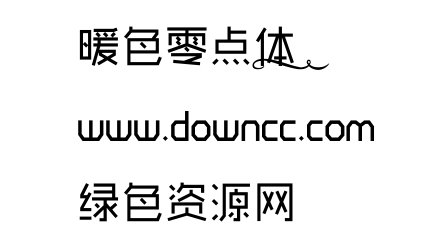
零點(diǎn)體是暖色君推出的一款藝術(shù)字體,在合體字體的基礎(chǔ)上添加了各種不同的修飾,讓文字變得個(gè)性十足,比起端正的宋體和楷書,顯得十分活潑,喜歡的歐陽(yáng)就來綠色資源網(wǎng)下載吧!
暖色零點(diǎn)體是由暖色君制作分享的卡通字體,字體間又裝飾上了漂亮的花紋,更加具有藝術(shù)感,將黑體字體進(jìn)行重新設(shè)計(jì),給人舒適搶眼的視覺效果,可以廣泛運(yùn)用于書面設(shè)計(jì)、文字印刷、海報(bào)設(shè)計(jì)等場(chǎng)合。